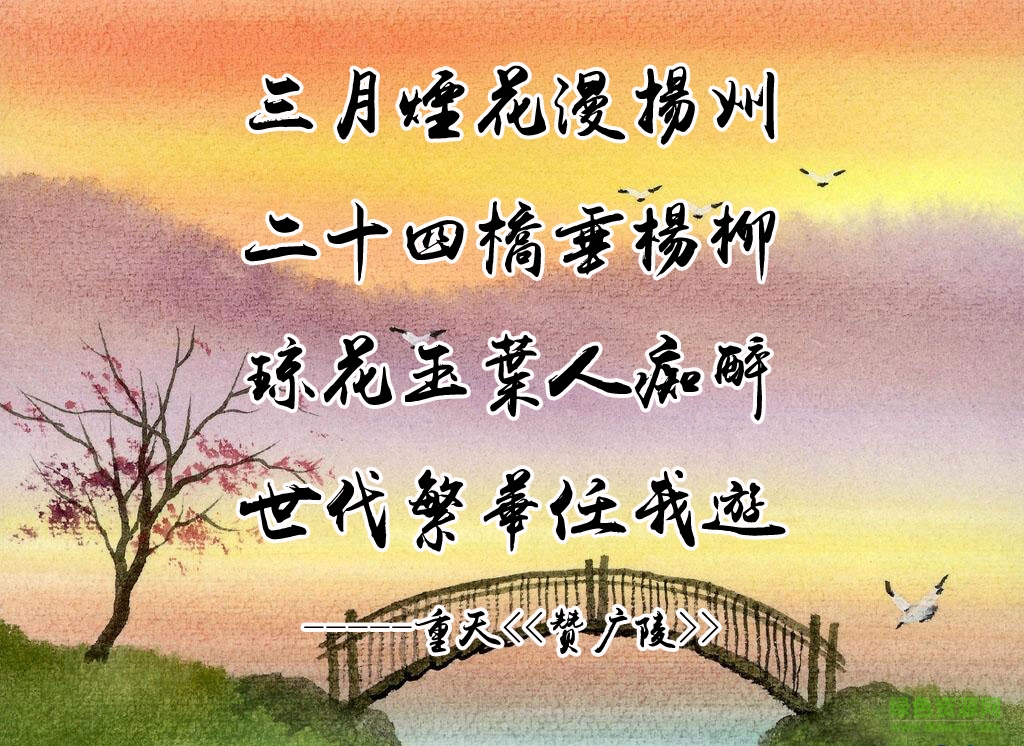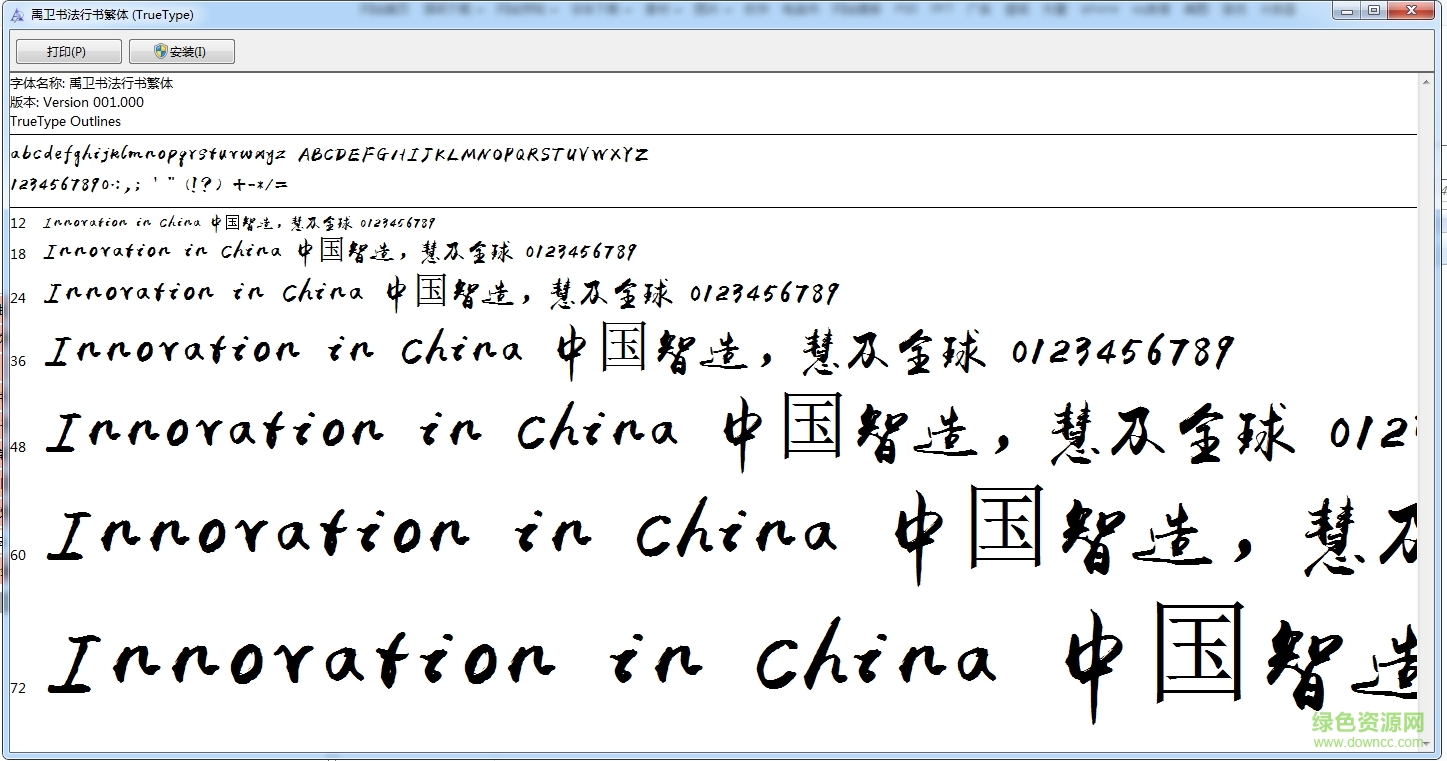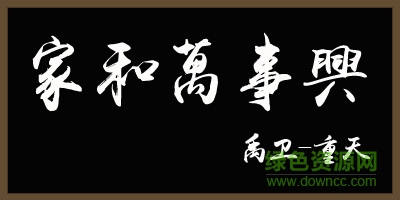
禹衛(wèi)書法行書繁體是由禹衛(wèi)先生書寫的一款繁體行書,該字體飄逸大方,粗細(xì)適中,包含了所有的常用字和生僻字,適合用在古風(fēng)場景,可應(yīng)用于平面設(shè)計(jì)、名片設(shè)計(jì)、廣告創(chuàng)意、印刷包裝等領(lǐng)域,喜歡的小伙伴快來綠色資源網(wǎng)下載吧!